WITH STAMP(ウィズスタンプ)
環境保全団体のWWFジャパンは、約2万4000種以上もの絶滅の恐れがある野生生物の新しい保護活動支援として、自分の名字とそれらの動物のシルエットが一緒になったスタンプが作れる「WITH STAMP(ウィズスタンプ)」キャンペーンを開始した。
専用サイトから自分の「名字」を入力するだけで、レッドリストに掲載された“絶滅の危機にある動物”をモチーフにしたシルエット入りのオリジナルスタンプを作ることができる。
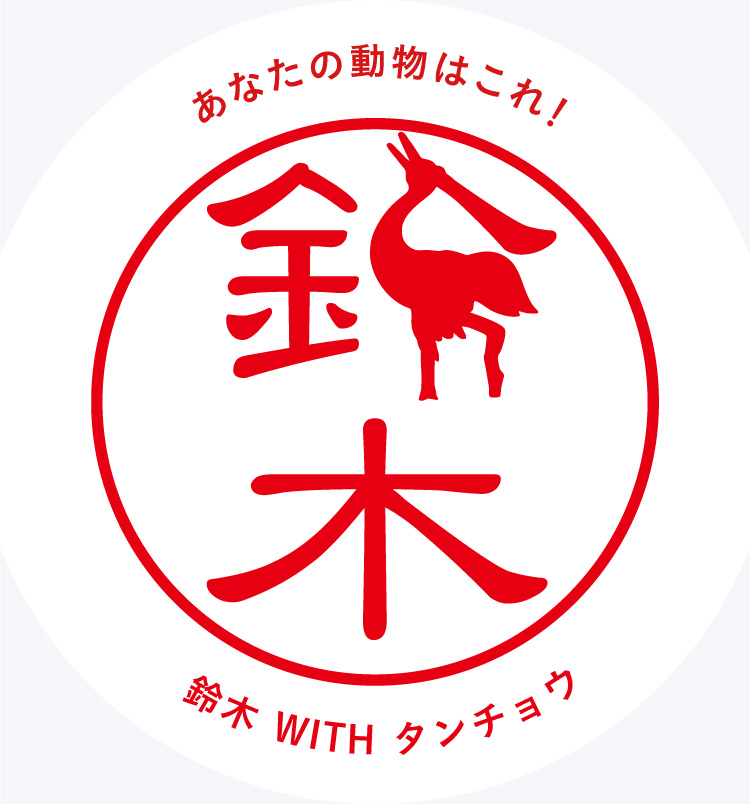
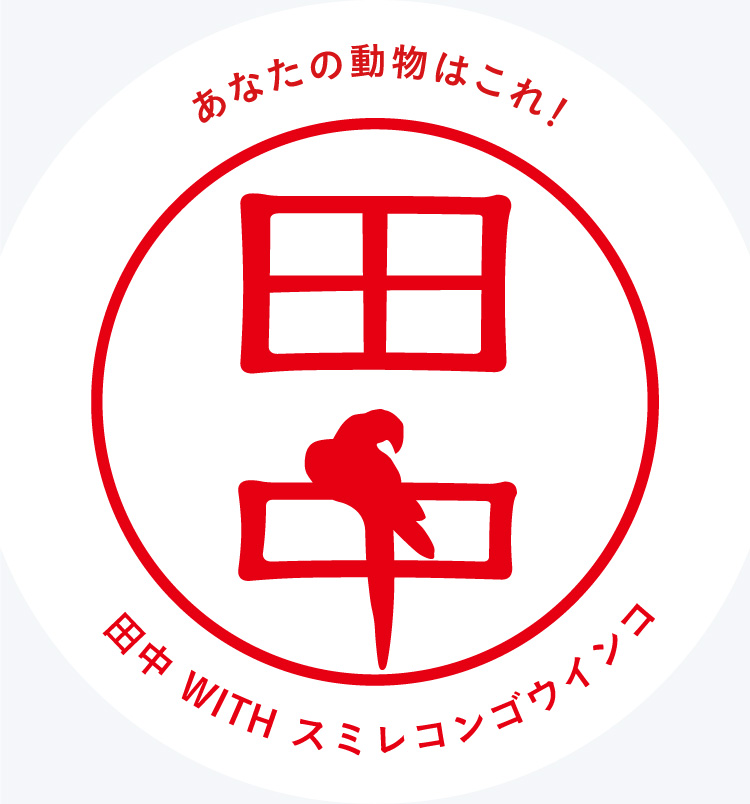
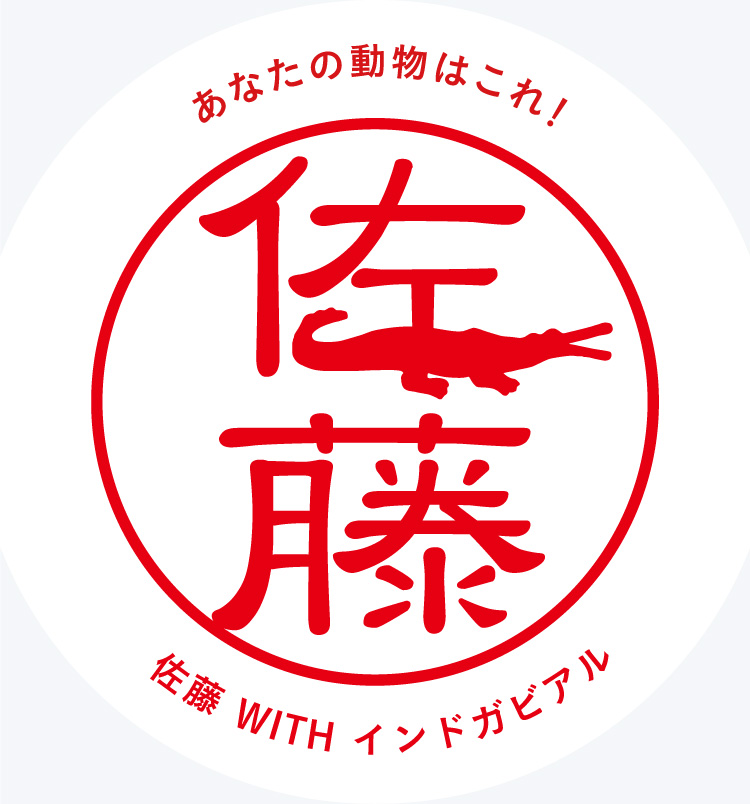
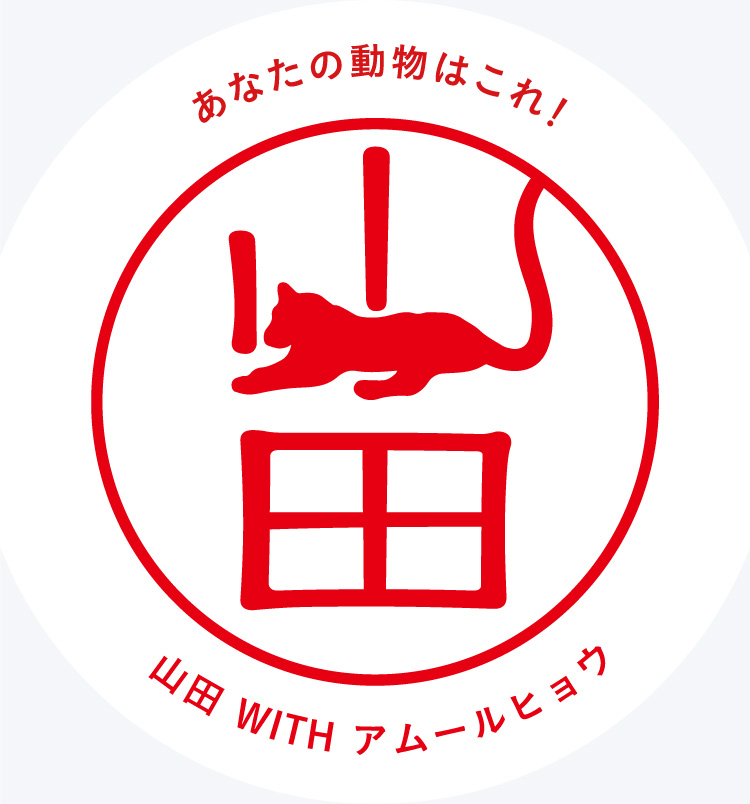
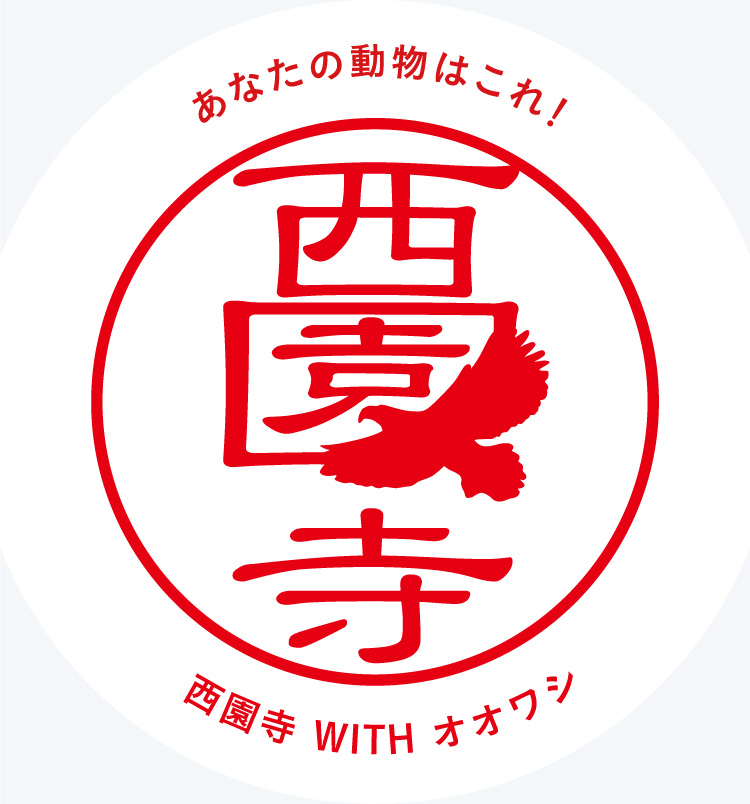
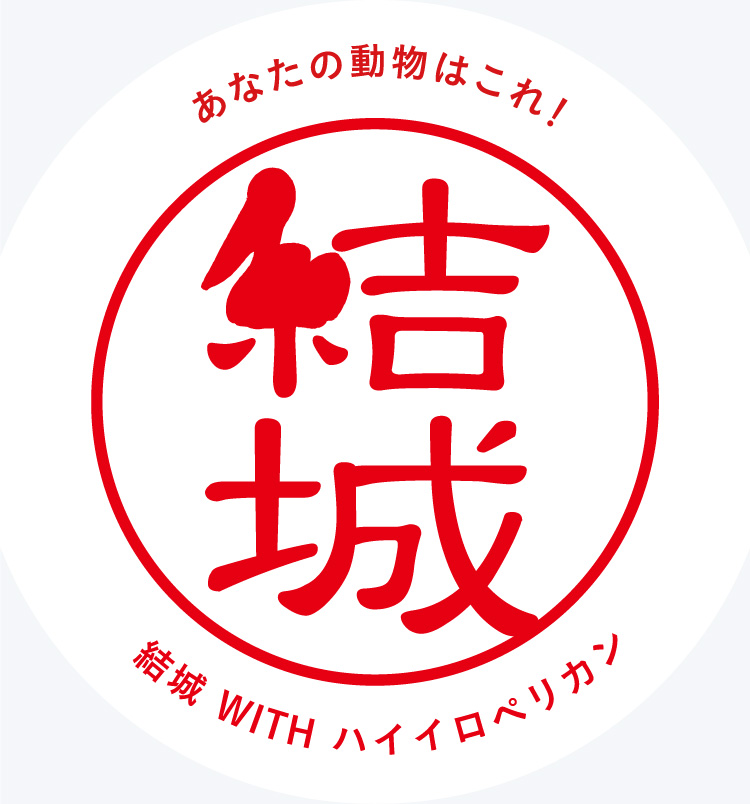
ちなみに表示に動物が入ってる人ではどうなるのかも検証してみた。
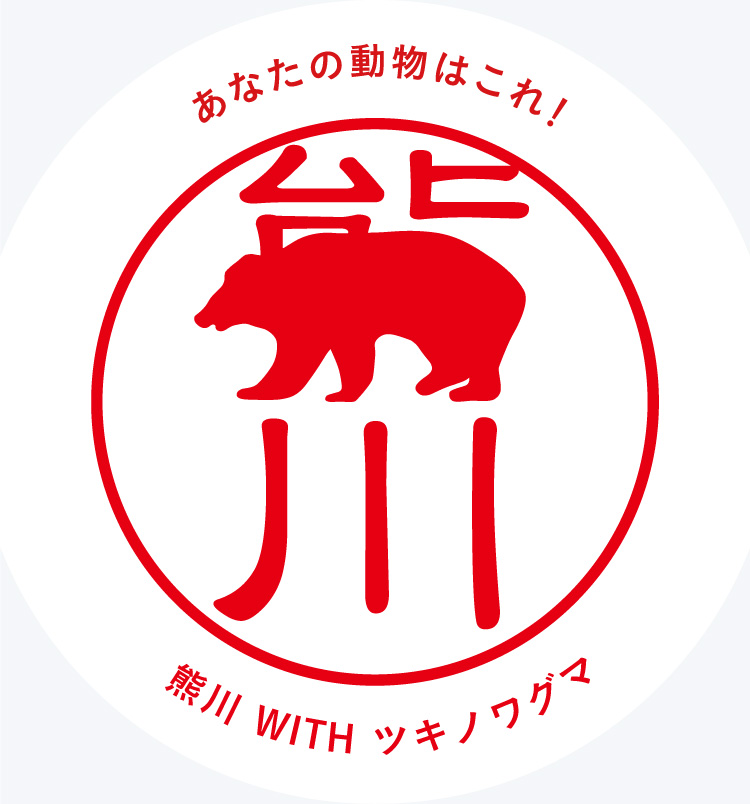
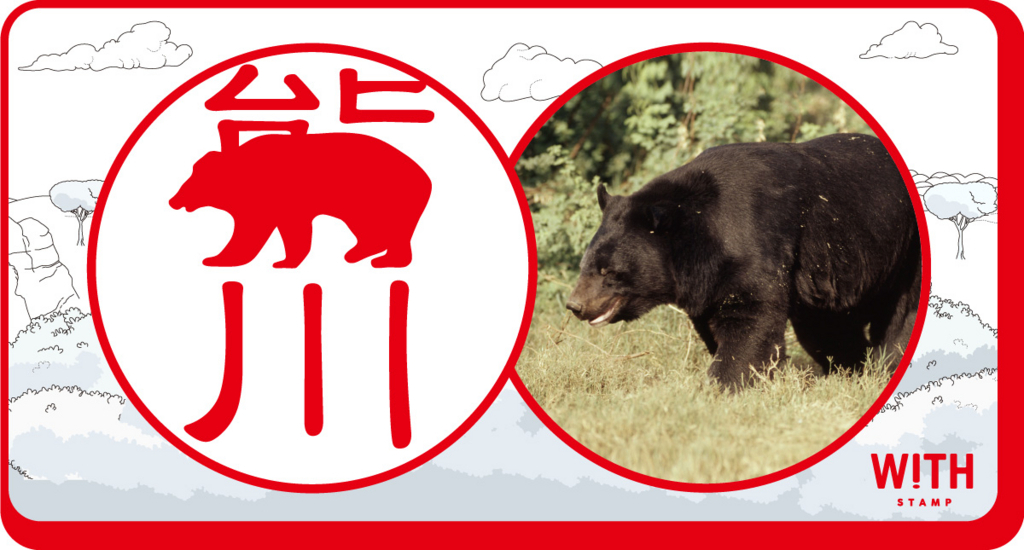
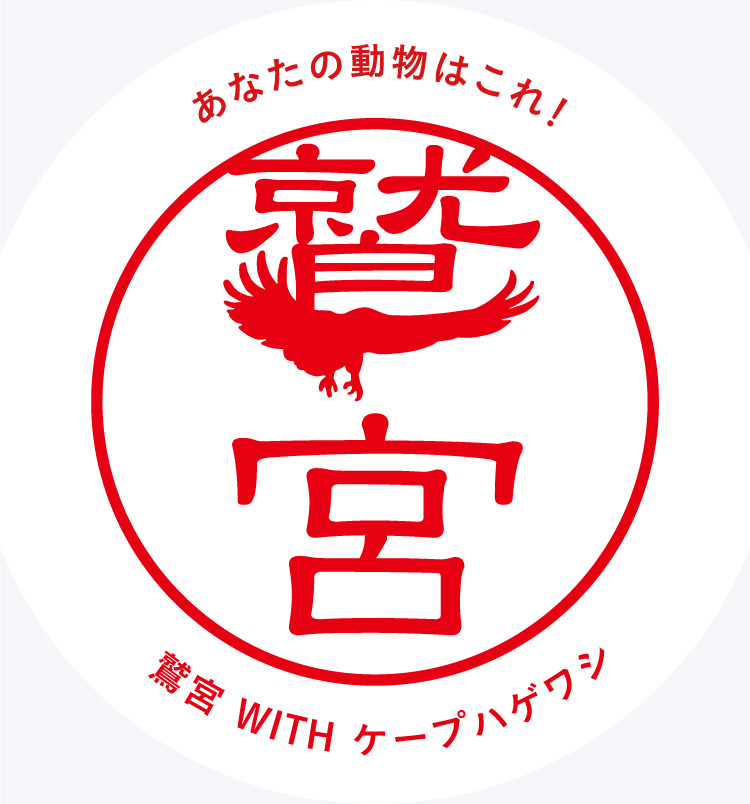
さすがに動物に引っ張られたようだ。
ついでに希少すぎる苗字の人間はこうなる。
打ち込んだ苗字は馬と鹿で馬鹿という苗字。馬鹿は絶滅のおそれがあるのかもしれない。
2万2000以上の名字に対応しており、予想外な位置に動物が現れることもある。
またその動物の写真に加えて表示される説明を読むことで、彼らの生態や現在の状況に関して知ることができる。もちろん購入したハンコは宅配便や領収書の認印など普段使いのハンコとして使用可能。
現在、カジュアルタイプを購入して使用しているが、自分はベローシェカだった。
ベローシェカ
レムール(キツネザル)と呼ばれる古い時代の特徴を残した霊長類の一種で大型のものが多いインドリ科に属する。マダガスカル島南東部に生息し、基本は樹上生活をしている。地上歩行が苦手で横飛び移動をする。森林の消失や、農地の開発などによって生息地を破壊されたことが原因で減少している。
ベローシェカも絶滅の危機があるそうだ…、踏みとどまってくれ!